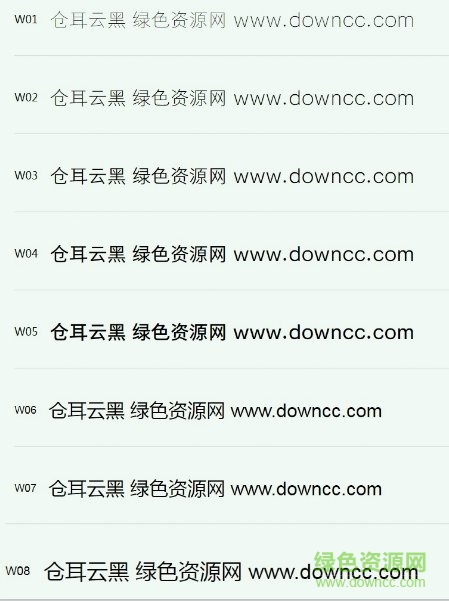
倉(cāng)耳云黑ttf是一款擁有八個(gè)字重的倉(cāng)耳字庫(kù)家族字體,作為首款黑體字體,簡(jiǎn)單大方的造型給人很舒適的閱讀體驗(yàn),八種規(guī)格個(gè)性鮮明,讓你的文字設(shè)計(jì)更加與眾不同,一起來(lái)綠色資源網(wǎng)下載吧!
倉(cāng)耳云黑是一套黑體家族字庫(kù),設(shè)計(jì)師以中國(guó)書(shū)法結(jié)體為基礎(chǔ),在筆形和結(jié)構(gòu)上都做了獨(dú)特的處理,在同樣字號(hào)時(shí)更易識(shí)別,閱讀輕松的同時(shí)還更符合漢字的審美習(xí)慣。
倉(cāng)耳云黑W01
倉(cāng)耳云黑W02
倉(cāng)耳云黑W03
倉(cāng)耳云黑W04
倉(cāng)耳云黑W05
倉(cāng)耳云黑W06
倉(cāng)耳云黑W07
倉(cāng)耳云黑W08